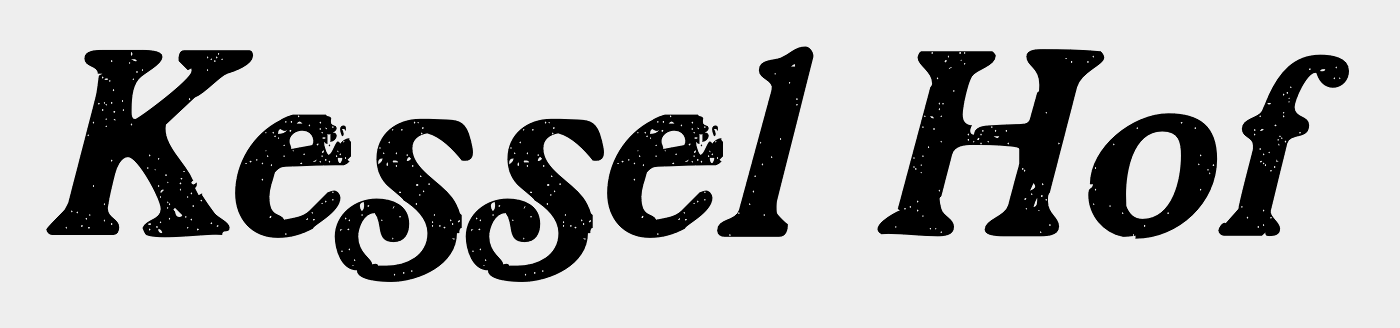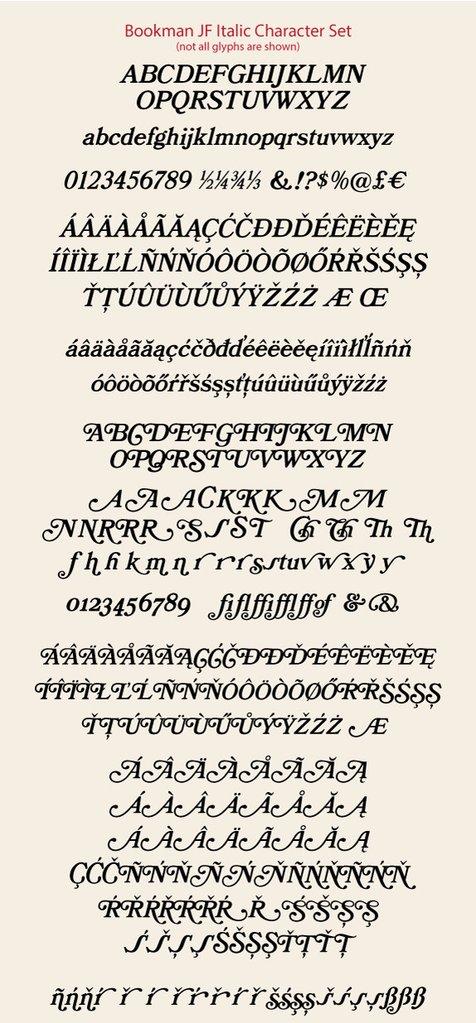
Suche die im Logo „Kesseltaler Hof“ verwendete Schrift
Der Scan dieses Logos stammt von der Visitenkarte der vormaligen Eigentümer. Diese hatten das Landhotel vor gut 25 Jahren übernommen. Ob das Logo damals entworfen/erstellt wurde oder zu dem Zeitpunkt auch schon existierte, weiß ich leider nicht.
Die Quetschränder lassen auf ein Klischee schließen. Das „a“ ist wohl aus der Schublade einer anderen Schrift „reingerutscht“, wobei es sich angesichts der Unterschneidung wohl nicht um Bleilettern handelt.
Auffällig sind das hohe „t“ sowie der hochsitzende Querstrich des „e“.
Auf die Schnelle nur jene gefunden:
Die hat das K und H mit Swash als OpenType-Funktion (kann hier wohl nicht als Text dargestellt werden) und kommt in dem kaputten Look daher. Ich meine aber, die Form des K mit diesem Swash schon irgendwo anders gesehen zu haben …
Sieht nach ziemlich viel Bastelei mit Fotosatz-Schriften von z.B. ITC aus.
Vielleicht besser das Helvetica-a entfernen und alles neu setzen? Bookmania auf Basis der Bookman wäre z.B. ein guter Kandidat. Die typischen Benguiat-Schwungbuchstaben sind enthalten.
Nach Bertels erstem Post las ich in der Beschreibung zur Scrubby auf myfonts.de: „The 1970s: an age of wonder, optimism and Bookman Italic. …“ Damit war ich dann auch schnell bei der Bookman Swash bzw. Bookmania. Ich habe hier sogar noch eine Bookman auf einer alten URW-CD gefunden. Allerdings mit einer recht großen x-Höhe und ohne Swashes. Dafür jedoch auch eine Version mit leicht abgerundeten Ecken (die URW damals für jede Schrift auf dieser CD mitlieferte), die durch die damalige Drucktechnik bei obigem Logo auch zu finden sind. Die ließen sich andererseits aber auch im Nu mit Illustrator erzeugen.